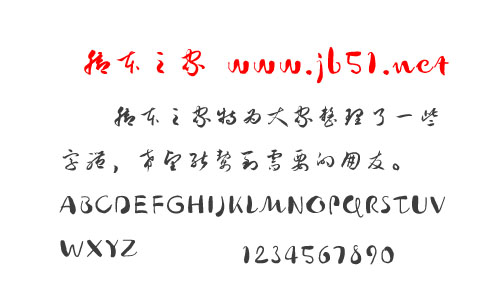
漢儀孫萬民草書字體(HYSunWanMinCaoShuW.ttf)是一款具有輕松風格的手寫現(xiàn)代書法字體,該字體在日常輕松書寫和傳統(tǒng)草書使用上找到了結合點,逐字書寫,賦予了字體手寫的溫度,并且可以更完美的實現(xiàn)各類終端環(huán)境的呈現(xiàn),能夠應用于文本裝潢、信息展示、網頁設計、篆刻制模、數據制作、裝潢設計、計算藝術設計、視覺設計、字帖等一切合法應用場景,本站提供了漢儀孫萬民草書字體下載地址,歡迎大家前來下載。